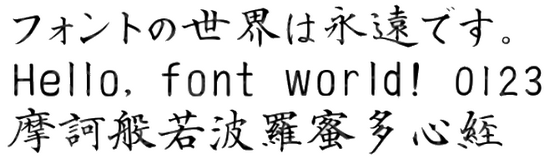
UD デジタル 教科書体 NP-R
- 等幅版あり
- 2 weight
- 一部で「奇跡のフォント」と言われる程の可読性
- でも教科書体では無い気が…
DFP教科書体RW3
- 等幅版あり
- 2 weight
- 文部省「小学校学習指導要領」に準拠した字形
- 一点一画まで習字を追求
DF超極太楷書体 StdN
- 等幅版(ttc版)あり
- 6 weight
- 楷書体で6書体も揃えているのはダイナフォントだけ
- 楷書体
- 隷書から転化した書体
- 「手本にする」の意で、公式文章で使用された
DF北魏楷書 StdN W3
- 等幅版(ttc版)あり
- 「龍門石碑体」をベースに、ウェイトを細く修正した書体
- 凛とした勢いを持ちながら、独特な気品を醸し出す
- 古風な感覚を喚起させた、冠婚葬祭などに最適な書体
- 六朝楷書(りくちょうかいしょ)
- 中国の南北朝時代、北朝で発達した独自の楷書体の総称
- 現在の楷書の起源となった書体の一
- 書道では楷書の書風の一つとしてとらえられている
- 現代中国では魏楷、北魏楷とも称する
DF文徴明体 Std W4
- 2 weight
- 等幅版(ttc版)あり
- 文徴明「千字文」の小楷をコンセプトに開発した秀逸な書体
- 文徴明とは明代の文人で、詩文・書画にすぐれた
DF翔鷹楷書 StdN W9
- 「しょうようかいしょ」
- 鷹が天空を駆け抜けるような印象を与える楷書体
- 伝統的な楷書に鮮明かつクリエイティブに満ちた筆致を取り入れ
- 力強さとスピード感を表現した運筆
- 正統性と個性を両立
NSK 白洲毛筆宛名楷書
- 宛名書き用に作成された楷書
- 自然で品のある読みやすい書体
- 年賀状、宛名書き等に
HG正楷書体-PRO
- Windowsでの楷書体標準
- 正楷書体
- 楷書を忠実に再現した活字書体のこと
- 「清朝体」とも言われる
武蔵賞状楷書体太
- 3weight
- 賞状用にデザインした楷書体
- 漢字を約13,850文字収録
- 法務省が制定している人名用漢字をすべて収録
MJO馬王楷書
- デザイナー:王超鷹
- 第一水準すべて+第二水準12字
- 1988年にマール社から発刊された「新楷書体」に掲載された書体をベースに製作
- クラシック且つ新味の毛筆フォント
- 英文カーニング調整済み
MJO兎臣楷書145
- 第一水準すべて+第二水準12字
- 「新味クラシック」の印象且つややポップ感を持つフォント
- 馬王楷書に同梱
- 非破壊的なボールド加工工程を馬王楷書に当てた書体
- 余裕のある場所だけに画が太い、すっきりした特太楷体
DF行楷書 StdN W5
HG羽衣M
- 4 weight
- 活字的なバランスで縦/横組を実現した筆文字
- 楷書体と行書体の中間的書体「行楷書」
TAS-相依為命体
- 第一水準すべて+第二水準約450文字
- 3 weight
- 4 family(正体/斜体/長体/平体)
- ラストエンペラーの実弟の書をフォント化
- 中国・清朝最後の皇帝愛新覚羅溥儀の実弟、溥傑の筆・約400文字を基にデザイン
- 流麗さが際立つ毛筆書体フォント
- 「相依為命」には「お互いに支え合いながら生きる」という意味が込められている
- 毛筆体で斜体/長体/平体は珍しいかと
DF痩金体 StdN W3
- 等幅版(ttc版)あり
- 痩金体
- 北宋の徽宗皇帝が考案した書体
- 細くて強い筆勢で元来「痩筋体」という名前がつけられた
- 皇帝に尊敬して「筋」を「金」に書き換えられた
DF古籍真竹A StdN W3
- 等幅版(ttc版)あり
- パッケージ『古籍五書体』
- グッドデザイン賞2014受賞
- 台湾の「故宮博物院」に収録された古籍から復刻
- 細長く真竹のような雰囲気
- 力強さとしなやかさが備わった書体
- パッケージ『古籍五書体』が2014年グッドデザイン賞受賞
DF古籍真竹B StdN W3
- 上記の仮名変更版
- 統一感が上がった気がする
- 個人的にはこちらの方が好み
DF古籍木蘭A StdN W3
- 等幅版(ttc版)あり